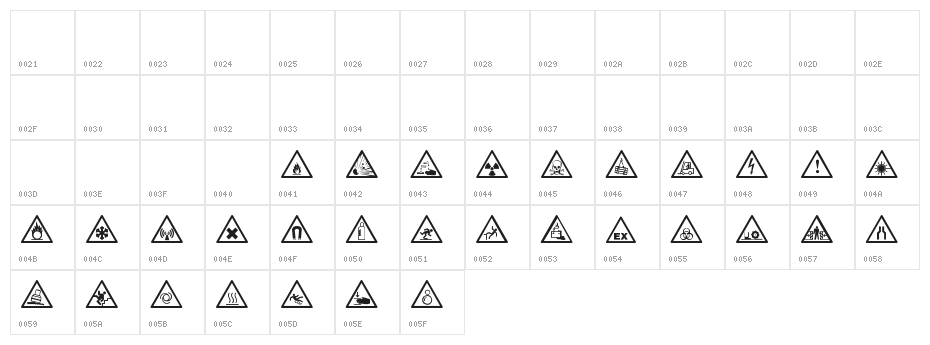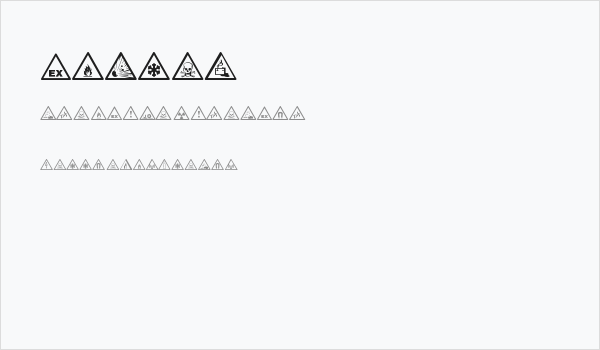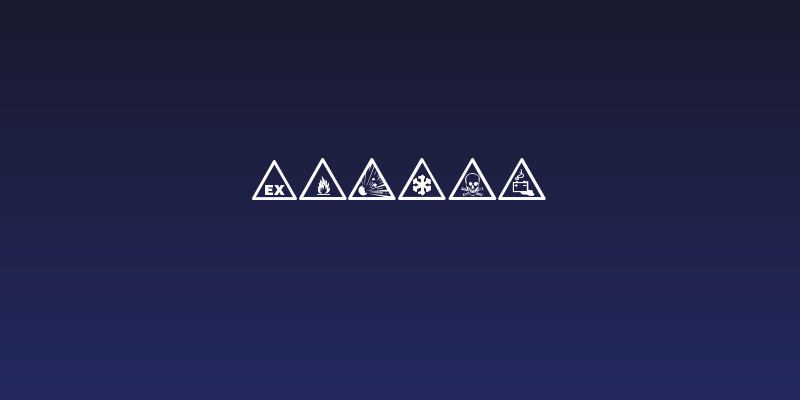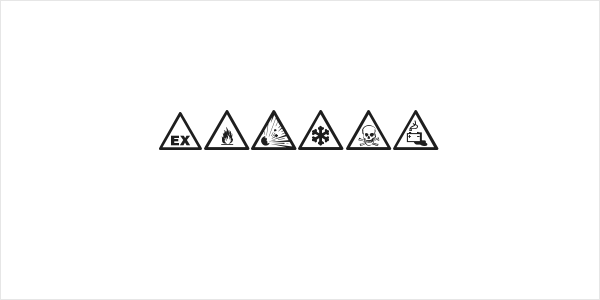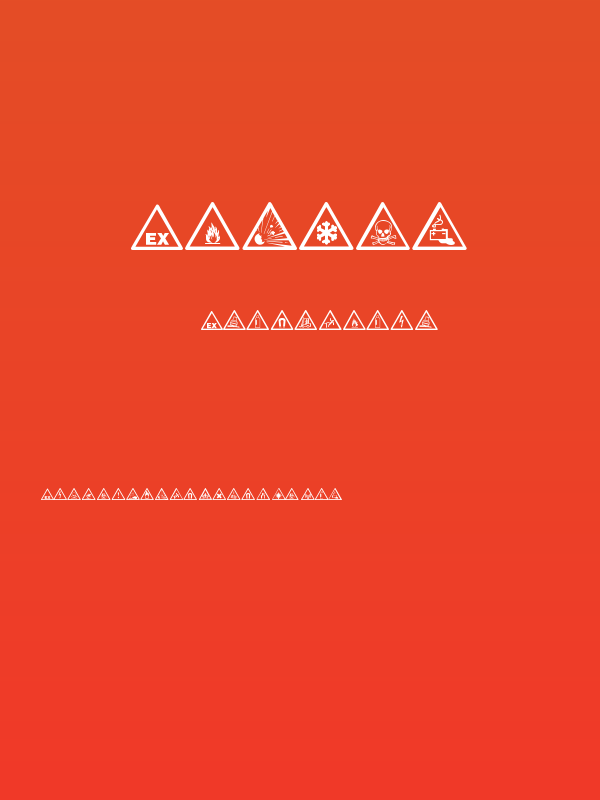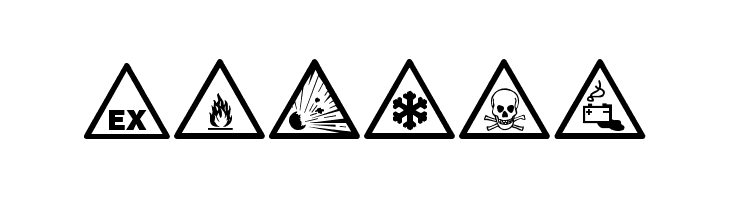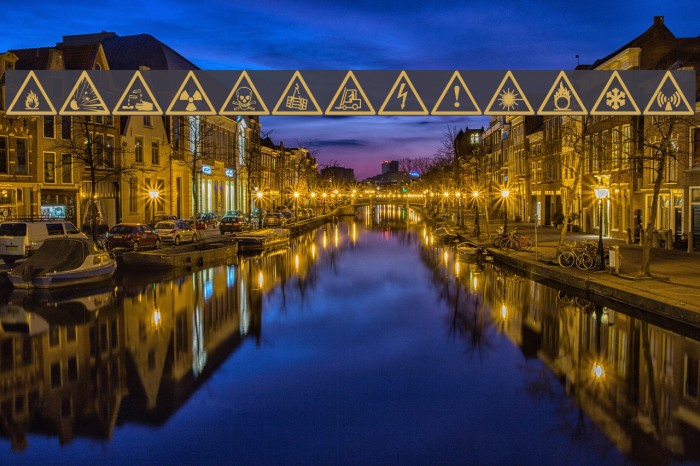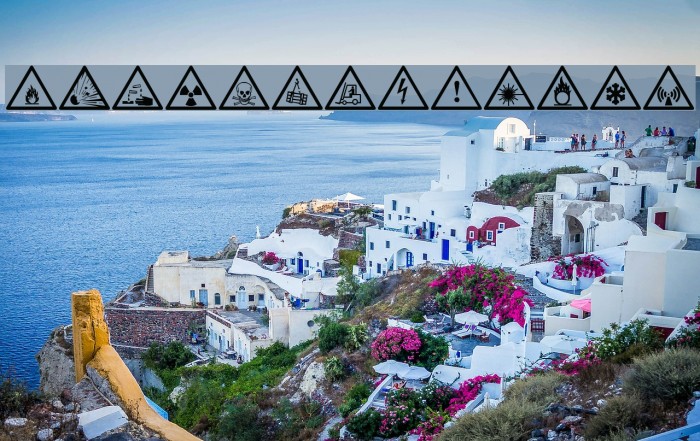
tables Font
✎ Dingbats
| カテゴリ | Dingbats |
| 全体的なスタイル | Functional, Modern, Industrial |
| 用途 | Warning signs, Safety instructions, Industrial labeling |
| おすすめプロジェクト | Safety signage, industrial warning labels, instructional materials, workplace hazard posters. |